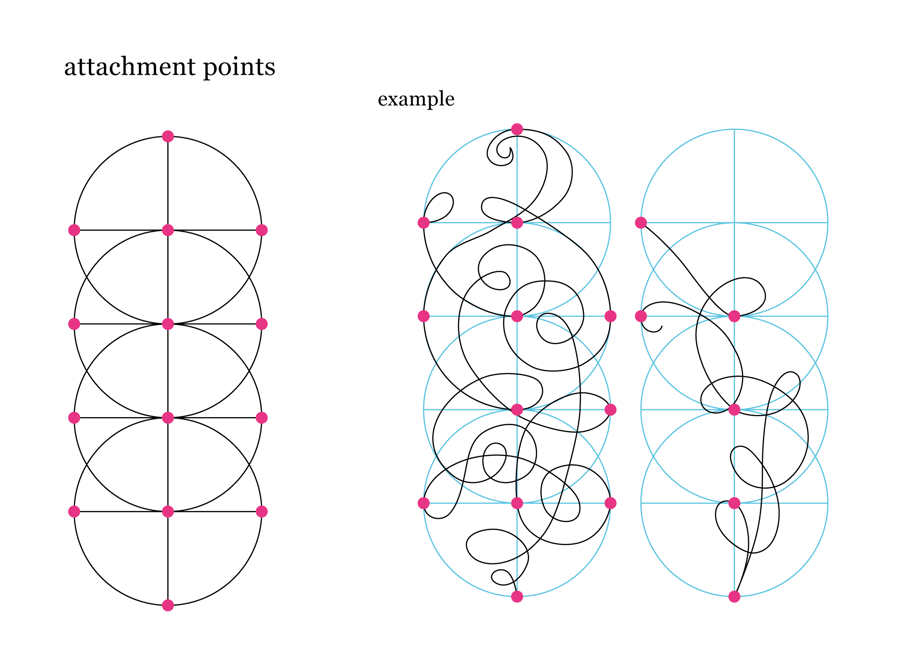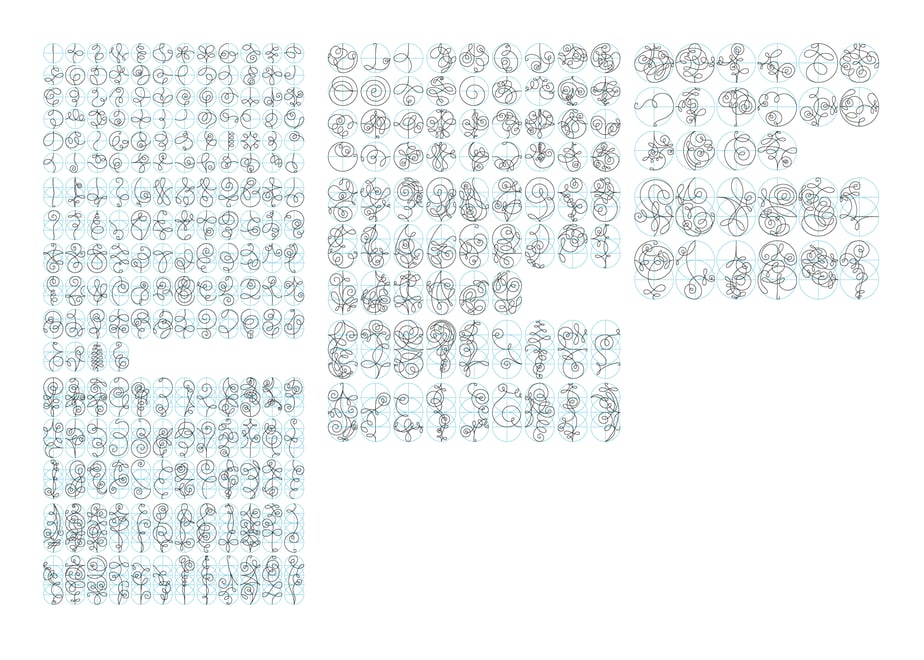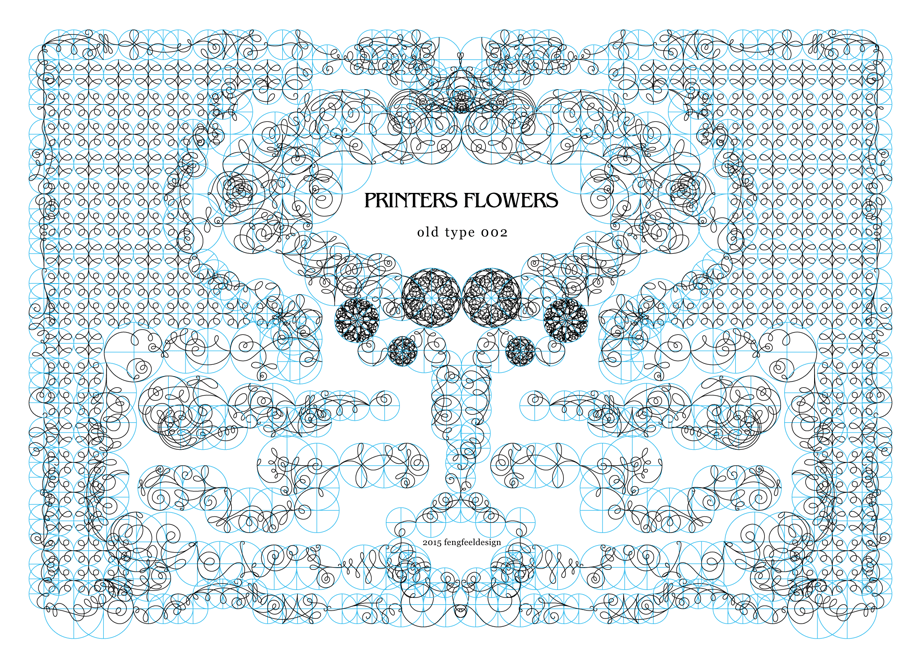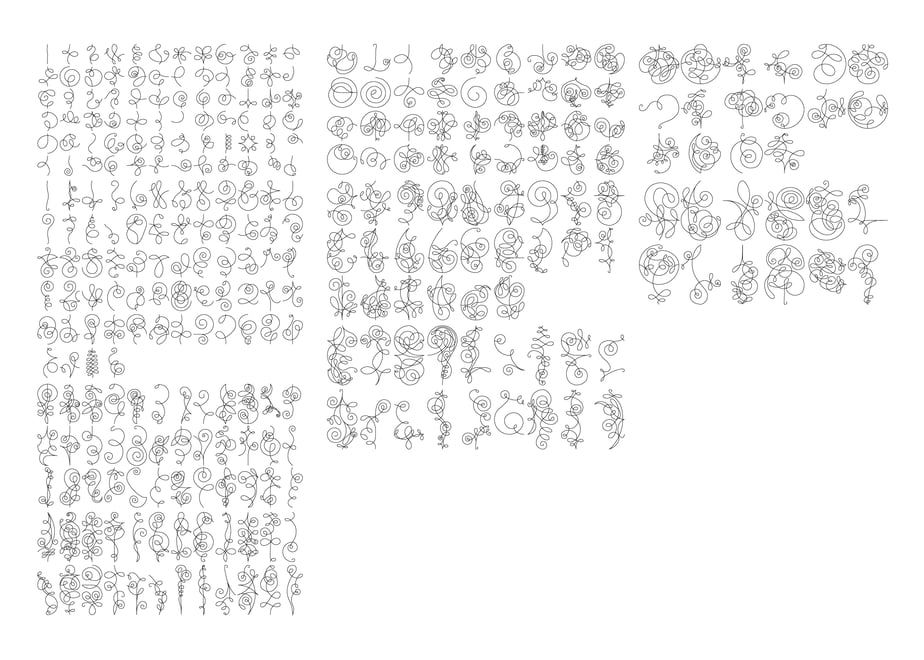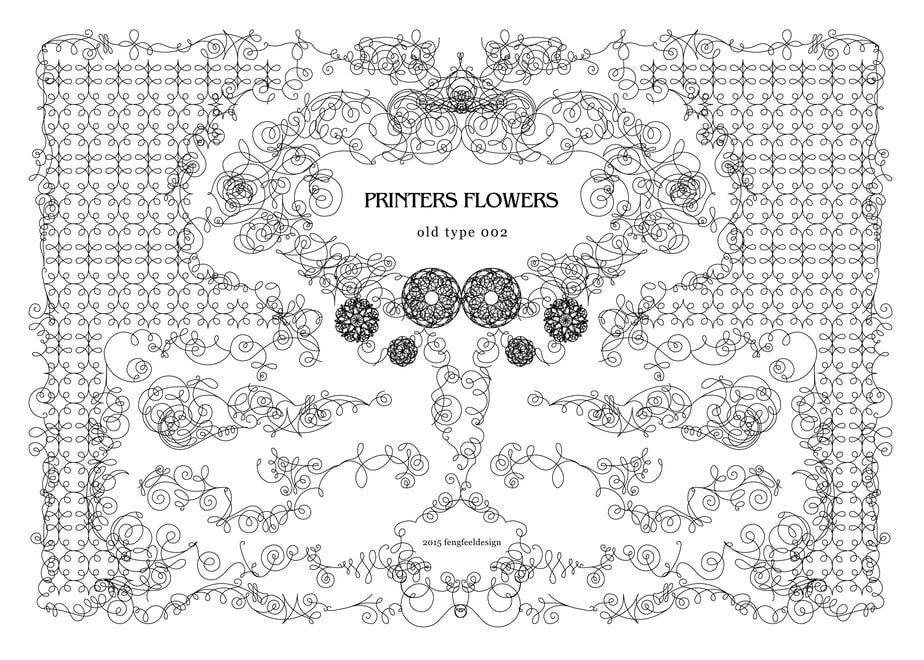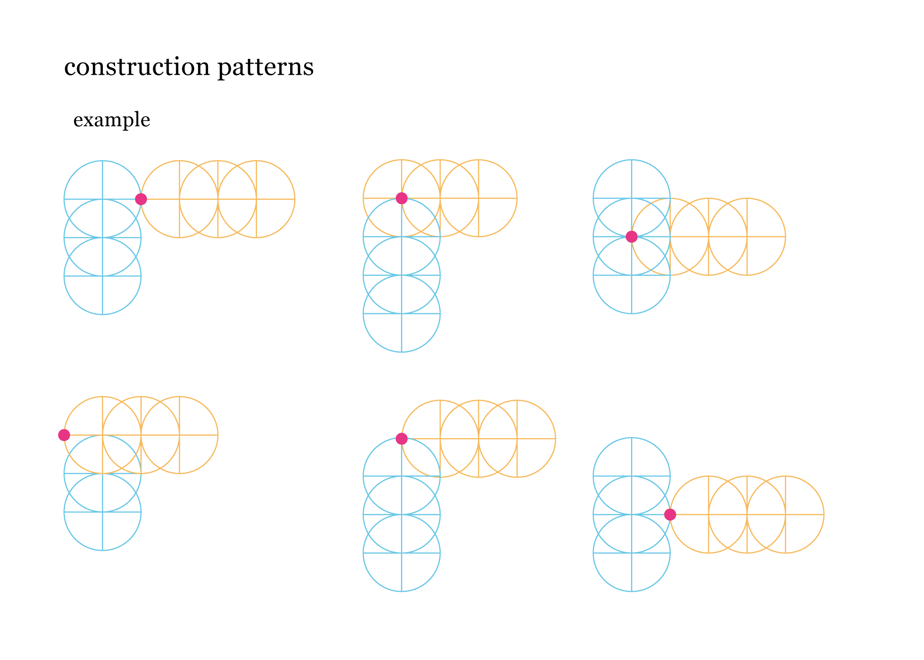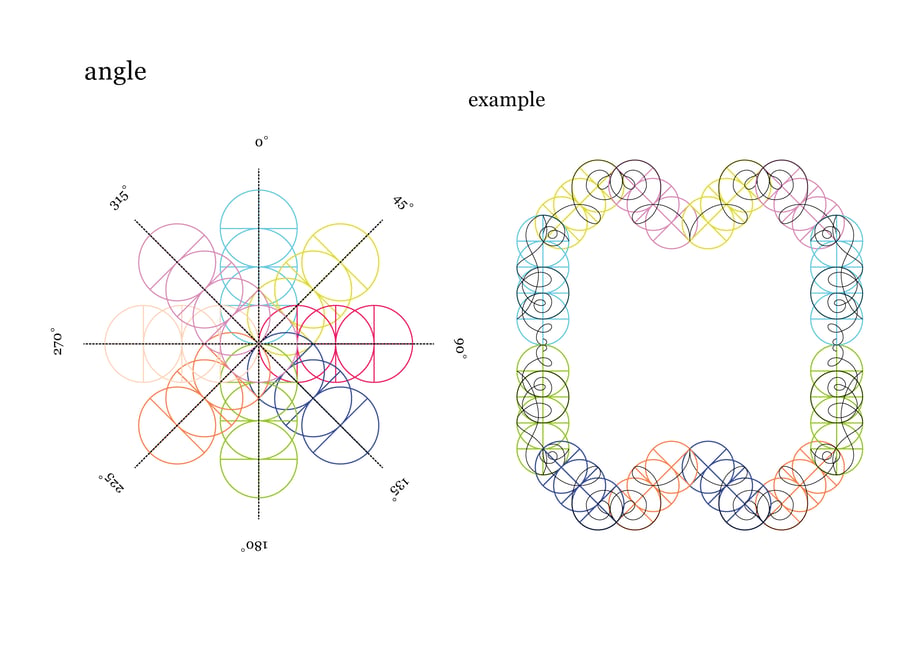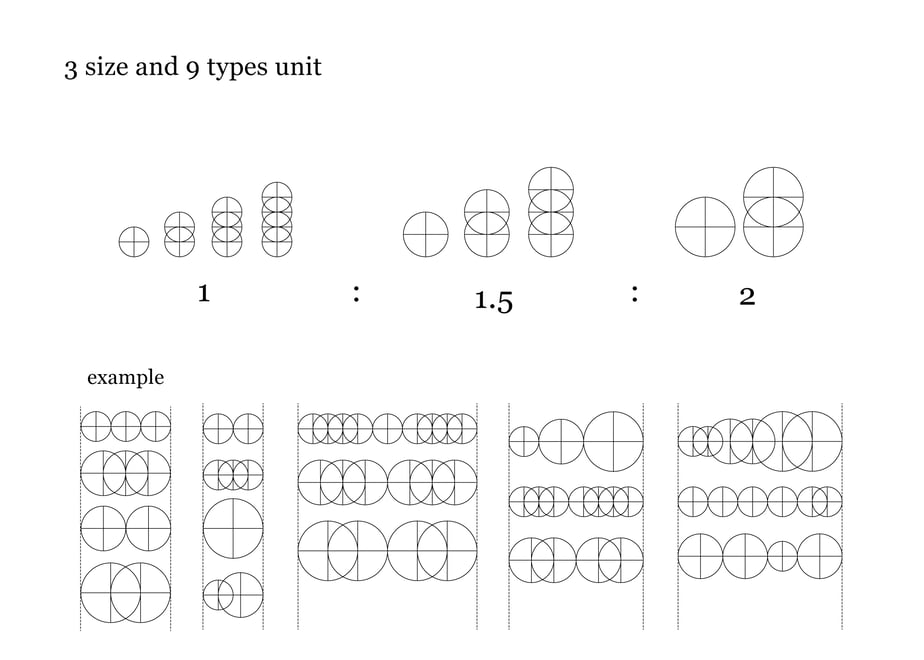
装飾活字:PRINTERS FLOWERS OLD TYPE 002
The classic decoration was built with a hug unit developed by fengfeel design. You can combine decorations more flexibly than the conventional square unit.
312 differently shaped objects, all outlined
古典的な装飾をfengfeeldesignが開発したhugユニットで構築しました。従来の四角のユニットよりも柔軟に装飾を組み合わせる事が出来ます。
全てがアウトライン化された312個の形の違うオブジェクト